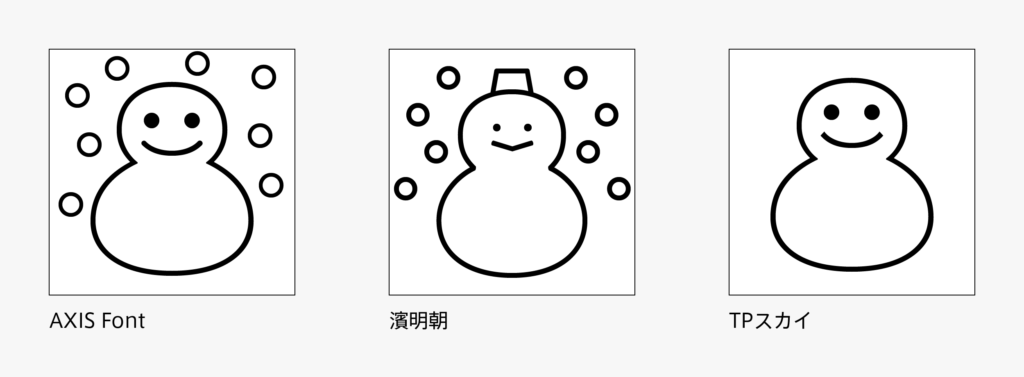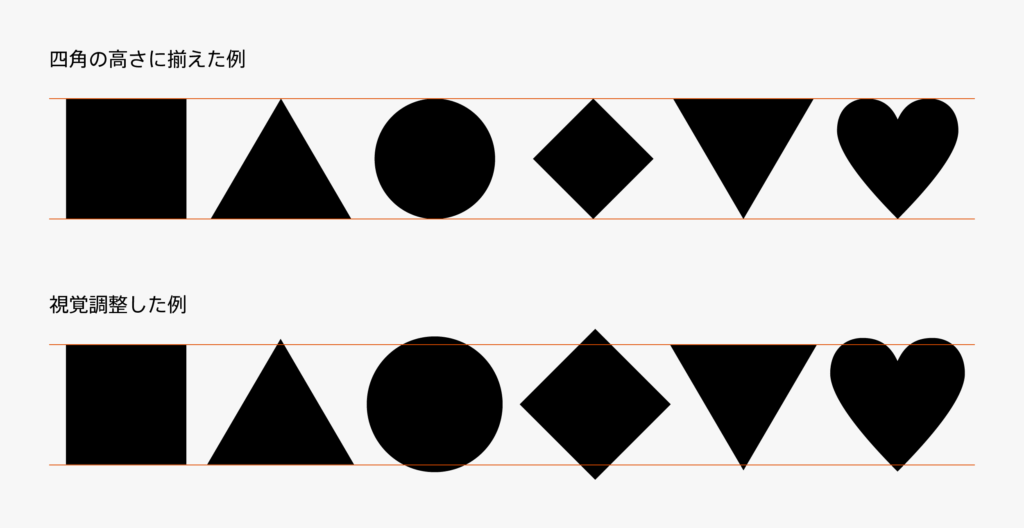
和文約物05「記号類」
丸・三角・四角のような図形や天気マークなど、収録されている記号類はフォントセットによって様々です。
図形は数値的に同じ大きさで揃えるのではなく、視覚的に同じような大きさに見せるのがポイントです。同じような大きさに見せるというのは、図形だけではなく他のグリフにも言えることです。タイポグラフィの基礎を学んだ際、まさにこのような図形で視覚調整の練習をしたことをよく覚えています(こちらの記事で紹介)。
天気マークはフォントごとの違いが面白いグリフかもしれません。フォントによっては太陽や雲にも顔がついていたりして可愛いのですが、タイププロジェクトのお天気マークは比較的シンプルで、顔がついているのは今のところ雪マークだけです。ついでに言うと、雪マークはAXIS Fontだと雪だるまに雪が降っていて、濱明朝の雪だるまは帽子つき、TPスカイは雪が止んで帽子もなしの雪だるまだけと最もシンプルです。